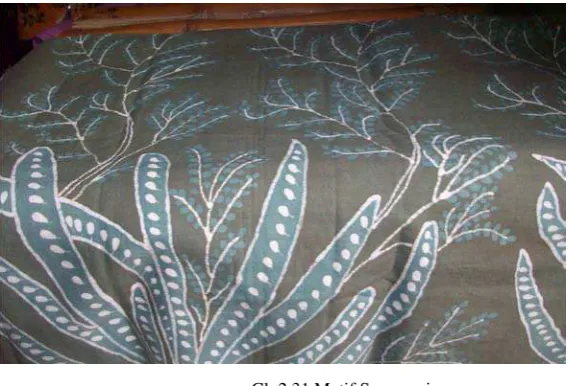
PERAN CAN GAN T Y PEFACE M OT I F BAT I K ECO
M AN GROV E
PERANCANGAN TYPEFACE MOTIF BATIK ECO
MANGROVE
PERANCANGAN TYPEFACE MOTIF BATIK ECO MANGROVE
ABSTRAK
Typeface batik mangrove ini di gunakan untuk memperkenalkan batik mangrove dan menambah koleksi typeface khas Indonesia yang masih sedikit. Batik mangrove merupakan salah satu batik kebanggaan masyarakat kota
Surabaya. Meskipun batik mangrove telah cukup lama berkembang, namun
keberadaannya kurang dikenal oleh masyarakat.
Batik mangrove merupakan satu-satunya batik di Indonesia yang sistem
pewarnaanya menggunakan tanaman bakau atau bisa di sebut alami dan motifnya
mewakili pesisir kota Surabaya. Upaya yang di lakukan untuk mempromosikan
batik, khususnya batik mangrove, yaitu dengan membuat typeface. Motif Batik mangrove khas Surabaya di gunakan sebagai elemen typeface. Daya tarik dari motif batik mangrove di harapkan dapat kenal oleh masyarakat melalui typeface
yang memiliki karakter budaya Indonesia
Konsep utama dalam perancangan ini mengambil ciri khas dari batik
mangrove, motif yang di ambil adalah ekosistem mangrove. Karena motif tersebut
menjadi motif yang paling menarik untuk di ambil dan motif ini juga bisa di
bilang motif utama pada batik mangrove yang ada. Motif yang di ambil ini
merupakan motif keseluruhan dari satu kain batik mangrove.
Konsep desain Typeface Motif Ekosistem Mangrove diharapkan mampu
mengajak seluruh mahasiswa dan masyarakat yang senang dengan dunia tipografi
agar menjadi sebuah inspirasi untuk membuat typeface baru
ABSTRACT
Batik mangrove Typeface is used to introduce batik mangrove and increase collection of typical Indonesian typeface which is still slightly. Batik mangrove is one of the surabaya society pride. Although mangrove batik has grown long enough, but its presence is less known by the public.
Batik mangrove is the only batik in indonesia which coloration system uses mangrove or it is called natural and the motif represent coastal of surabaya city. The effort made to promote batik, especially batik mangrove, is by create typeface. The motif of batik mangrove typical of surabaya is used as the element of typeface. The attractive of batik mangrove motif is expected can be known by the public through a typeface that has the character of Indonesian cultur.
The main concept in this design is taking from the characteristic of batik
mangrove. The motive taken is mangrove ecosystem. The motive becomes the most
interesting motive and it is also called the main motive of the existing batik
mangrove. It is the whole motive of the batik mangrove cloth.
The concept of typeface design mangrove ecosystem motive is expected to
invite all students and society who love and concern in typography in order to be
3.6 Kerangka Berpikir
Tabel 3.3 Kerangka Berpikir
Perancangan typeface eco mangrove
Fenomena Survey Riset Pasar
batik mangrove yang tidak memiliki identitas yang batik di surabaya terutama batik mangrove .
masyarakat Surabaya membutuhkan typeface tentang Surabaya.
masyarakat Surabaya yang tidak mengertinya akan keberadaan Batik mangrove khas Surabaya.
Rumusan masalah Judul